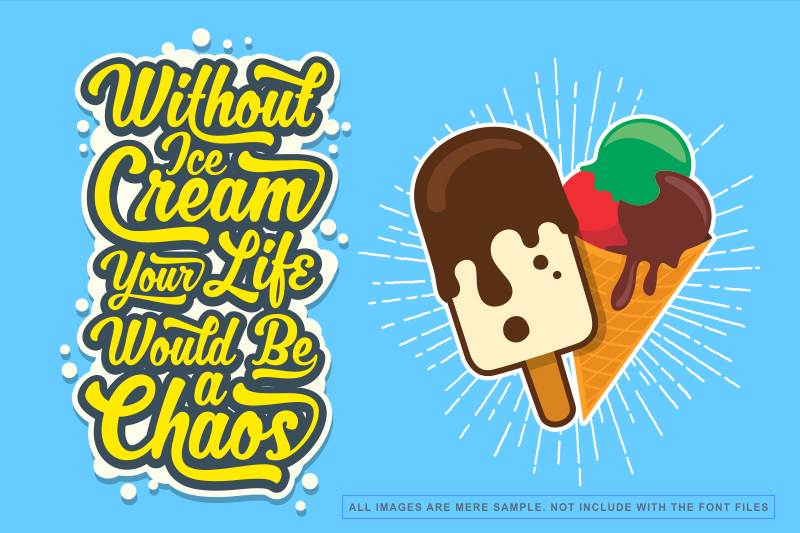
A MJF Zhafira é uma fonte de exibição perfeita para aqueles que buscam um equilíbrio entre modernidade e elegância. Com a categoria Display Fonts, essa fonte foi projetada com um designer habilidoso chamado Hamilton. Ela oferece duas características únicas: “Ligature” e “Contextual Alternates”. Essas opções adicionam profundidade e personalização ao seu design, permitindo maior flexibilidade na criação de layouts gráficos. A MJF Zhafira é uma escolha inteligente para quem procura um recurso adicional sem comprometer a qualidade. Porém, vale ressaltar que apenas o versão gratuita da fonte suporta essas duas características especiais.